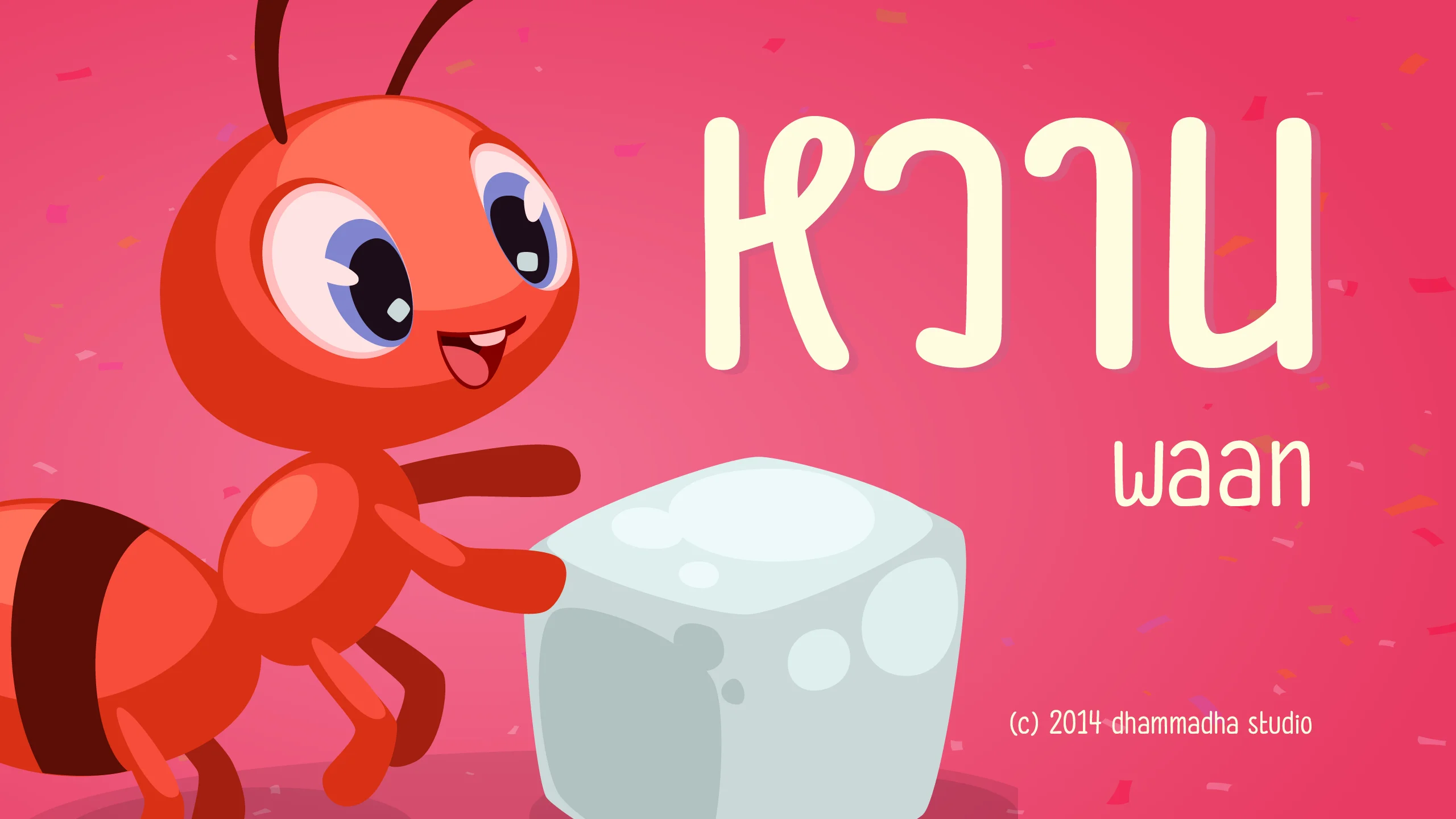
"หวาน | waan" คือฟอนต์ที่ถ่ายทอดความมีชีวิตชีวาผ่านลายเส้นอันเป็นธรรมชาติของปากกาไวท์บอร์ด โดยเน้นความต่อเนื่องพริ้วไหวและความหนาบางที่เกิดขึ้นจากการลากเส้นจริง ให้ความรู้สึกที่อบอุ่นเป็นกันเองเหมือนงานเขียนมือ (Handwriting) ที่มีความอ่อนโยน แต่แฝงไว้ด้วยความสนุกสนาน เหมาะอย่างยิ่งสำหรับงานออกแบบที่ต้องการสร้างความใกล้ชิดและสื่อสารอย่างจริงใจ ช่วยเติมเต็มอารมณ์ความรู้สึกให้งานดีไซน์ดูละมุนตาและมีเอกลักษณ์เฉพาะตัว ด้วยบุคลิกที่ดูสบายตาแต่ยังคงความชัดเจน ฟอนต์ชุดนี้จึงออกแบบมาให้ใช้งานได้อย่างหลากหลาย ตั้งแต่การทำคอนเทนต์บนโซเชียลมีเดียที่ต้องการความเป็นกันเอง งานประกอบภาพถ่าย ไปจนถึงสื่อโฆษณาที่เน้นความสดใสและดูมีชีวิตชีวา "หวาน | waan" จะช่วยให้งานออกแบบของคุณมีจังหวะการเล่าเรื่องที่ดูเป็นธรรมชาติและเข้าถึงง่าย สร้างบรรยากาศที่ผ่อนคลายและน่าจดจำในทุกการสื่อสาร